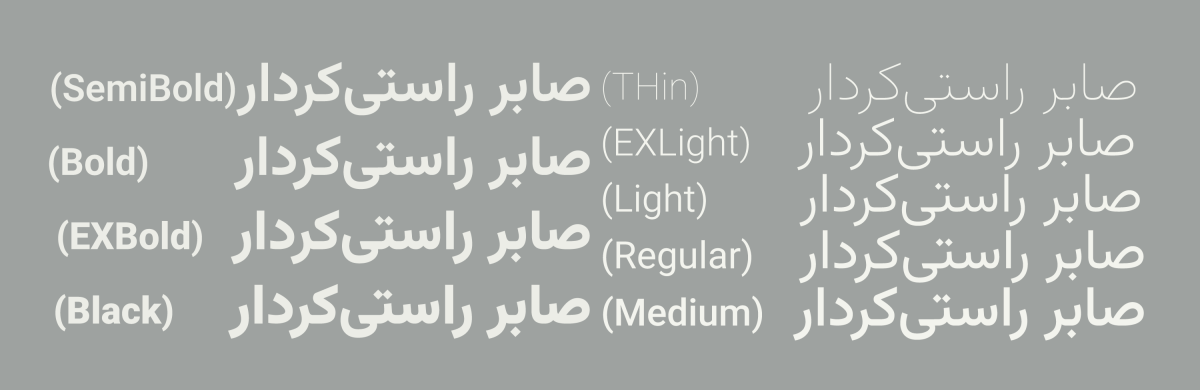
صابر راستیکردار خالق فونتهای آزاد (فونت وزیر، فونت صمیم، فونت، ساحل و…)
صابر راستی کردار پس از ماهها مبارزه با سرطان در تاریخ ۲۳ آبان ۱۴۰۲ درگذشت. او به دلیل طراحی فونتهای آزاد متعدد در جامعه طراحان و برنامهنویسان ایرانی چهرهای شناخته شده بود.
اگرچه طی سالهای اخیر، فونتهای فارسی بسیاری طراحی و عرضه شده است اما اکثر آنها دارای کپیرایت هستند. جامعه نرم افزار متنباز نیازمند فونتهایی با مجوز آزاد بود. فونتهایِ آزادِ “صابر راستیکردار” این مشکل را رفع کرد.
فونتهای آزاد کمک میکند تا توسعه دهندگان بدون نگرانی از مسائل مجوزها و مشکلات حقوقی، پروژههای خود را توزیع کنند و همگان در توسعه آنها مشارکت داشته باشند. فونتهای صابر راستیکردار با این هدف ساخته شده و همه با مجوز آزاد منتشر شدهاند.
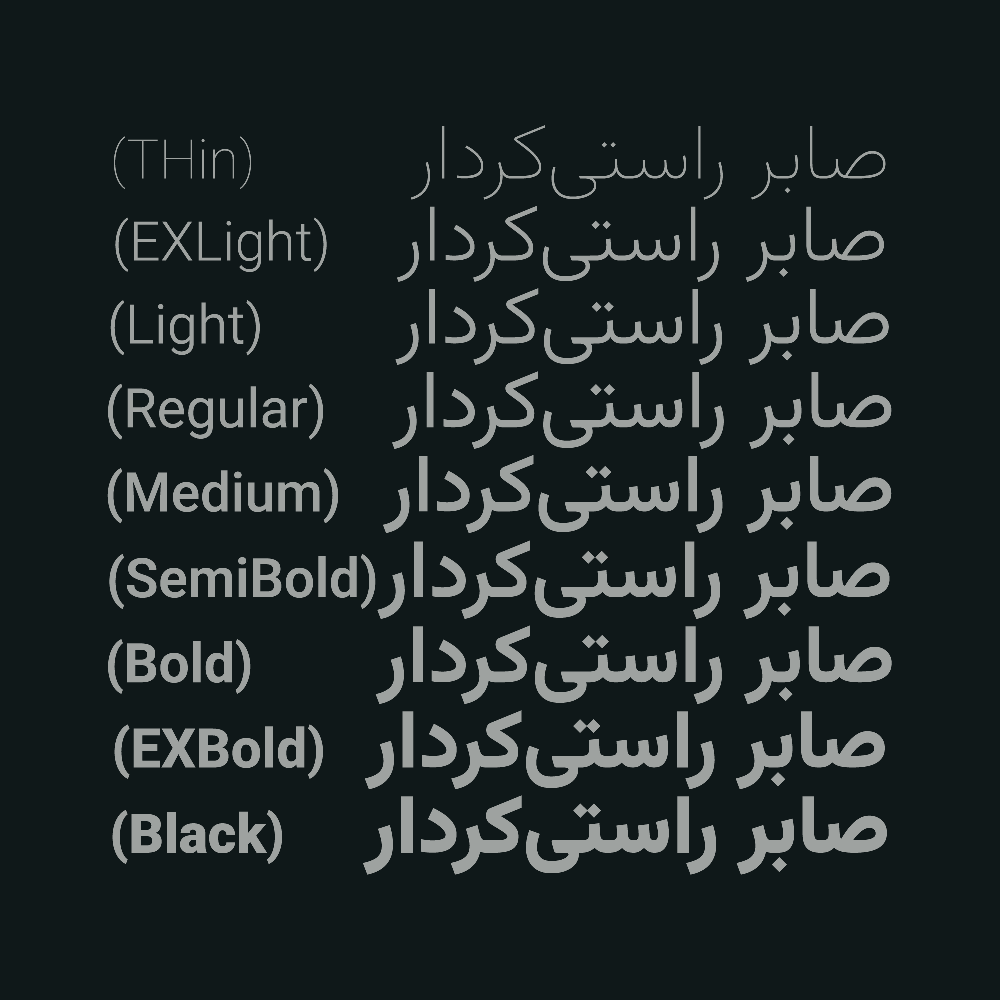
فونت وزیر شناخته شدهترین فونت صابر راستیکردار است که در وبسایتها و نرم افزارهای بسیاری استفاده شده. این فونت در سال 2022 به مجموعه فونتهای آزاد گوگل اضافه و همچنین به عنوان فونت فارسی نرم افزار تلگرام انتخاب شد.
فارسی زبانان تاهمیشه قدردان زندگی موثر او خواهند بود.